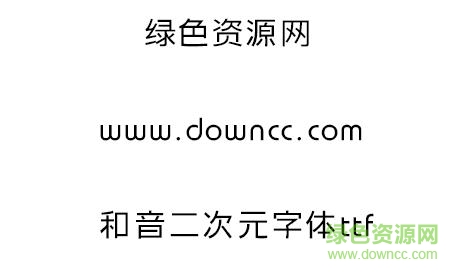
和音二次元字体ttf是一款混搭二次元字体,这款字体将二次元字体进行了缩小,同时混搭了其他的字体效果,让你感觉到更加不错的使用体验,这款字体在二次元界广为流传,受到万千二次元小伙伴喜爱,快来绿色资源网下载吧!
这款字体的最大特色在于能够带给喜爱字体的用户们韩很舒适的视觉享受,这款字体在规整中带着圆润,同时汉字与英文表现效果又大有不同,十分好看!